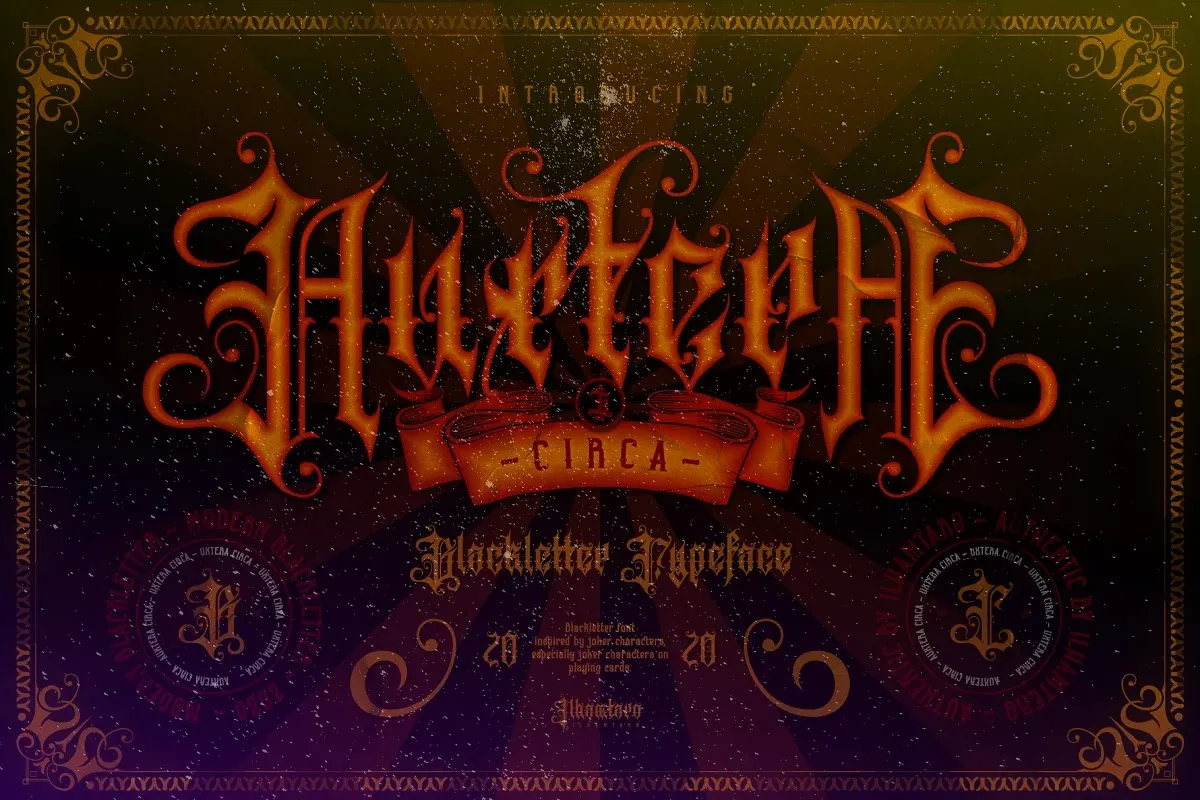
Auxtera Circa Font – Fonte Grátis
Auxtera Circa Font
A ‘Auxtera Circa Font’ é uma fonte blackletter única criada por ilhamtaro com influências do estilo victoriano. Esta tipografia se destaca em diversos contextos, especialmente aquelas que valorizam um aspecto vintage e elegante. Através de sua arquitetura complexa e detalhada, esta fonte é perfeita para quem aprecia designs de tatuagens e busca uma combinação única com ornamentos. Embora não seja apropriado para uso em parágrafos, essa fonte se destaca como um elemento de arte no design digital ou até mesmo como parte de uma coleção única de fontes digitais. Ela também é ótima para o design de rótulos de bebidas alcoólicas e capas de livros de banda de metal. Com sua complexidade e arquitetura, a ‘Auxtera Circa Font’ se destaca como uma opção exclusiva e inovadora no mundo das fontes blackletter.